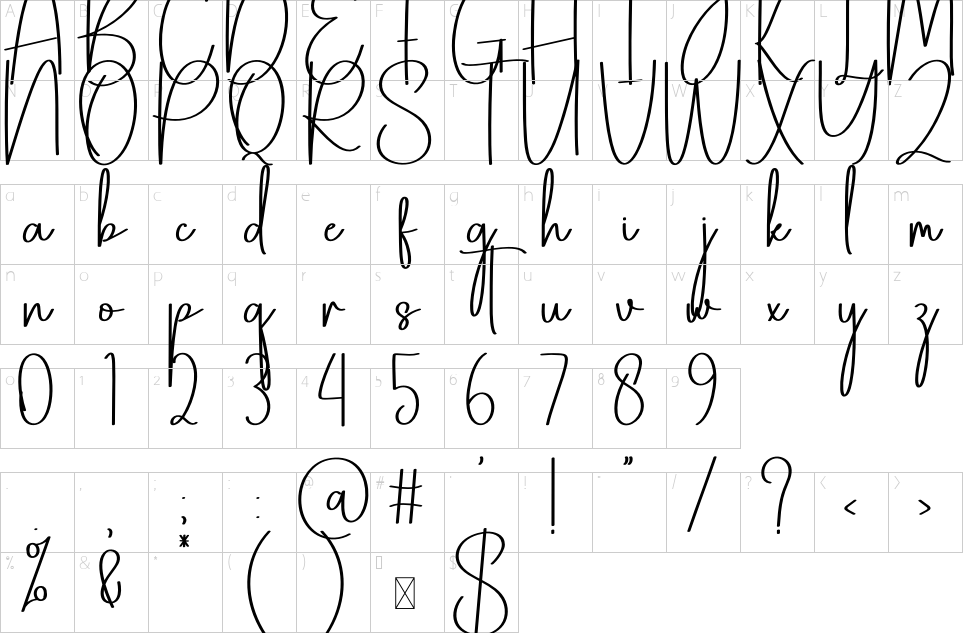
Baixar a fonte Midjourney para o Windows e Mac é uma excelente opção para quem procura um recurso de texto moderno e sofisticado. Midjourney é uma fonte criada por scratchones, que tem agradado muitos designers ao longo dos anos por seu design intuitivo e elegante. Com sua versão gratuita disponível, é uma fonte perfeita para projetos pessoais, freelancers ou até mesmo pequenos negócios que procuram adicionar um toque de sofisticação aos seus materiais digitais. Midjourney foi baixada 405 vezes, um número que prova seu valor e utilidade. Seja para criar materiais de marketing, design gráfico ou simplesmente fazer textos mais atraentes e profissionais, esta é uma fonte que vale cada download. Se você está procurando por uma fonte de qualidade e versão gratuita, Midjourney é uma ótima escolha.